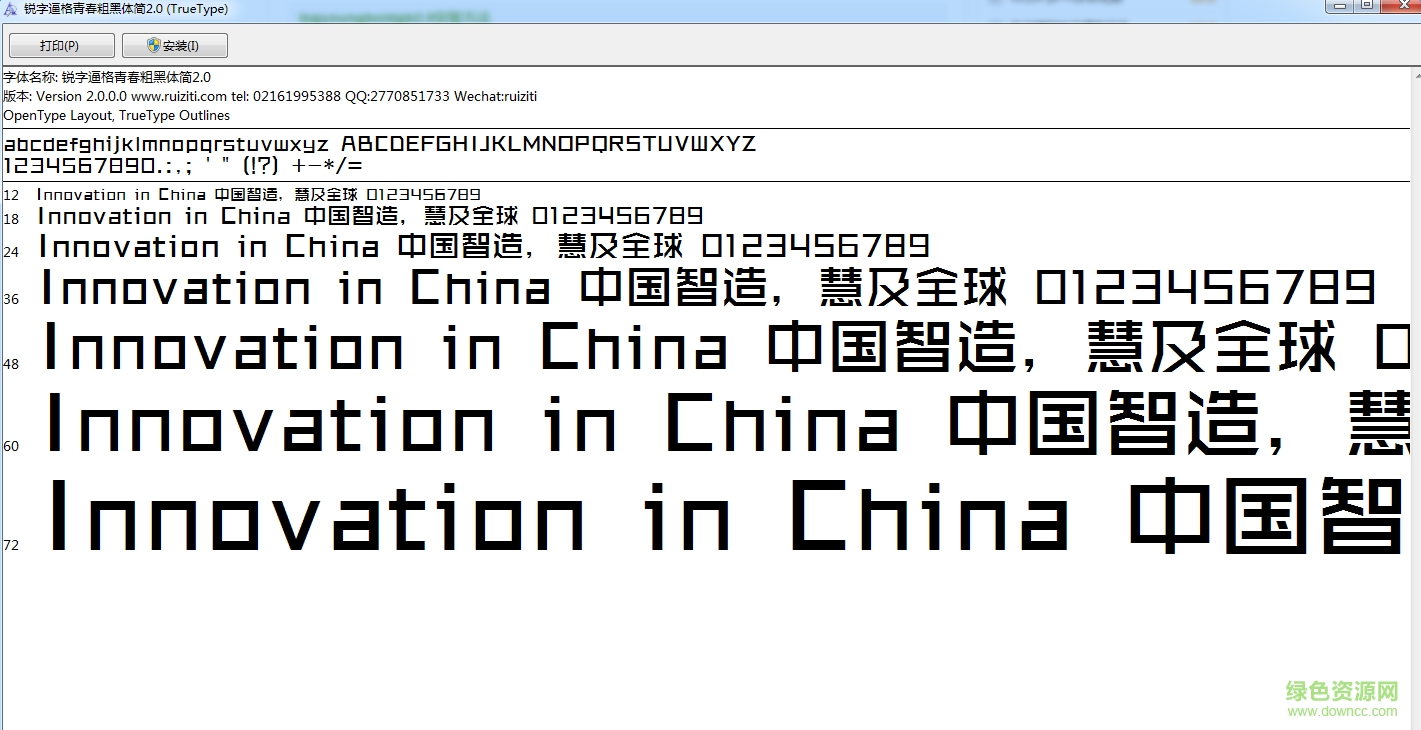
bigyoungboldgb2.0是什么字體?bigyoungboldgb2.0就是逼格青春粗黑體簡2.0的英文名稱,字形簡潔規(guī)整,筆畫干凈利落,閱讀效果良好,可用作報刊雜志的正文用字,歡迎大家在綠色資源網免費下載!
運用夸張、明暗、增減筆劃形象、裝飾等手法,以豐富的想象力,重新構成字形,既加強文字的特征,又豐富了標準字體的內涵。同時,在設計過程中,不僅要求單個字形美觀,還要使整體風格和諧統(tǒng)一,理念內涵和易讀性,以便于信息傳播。